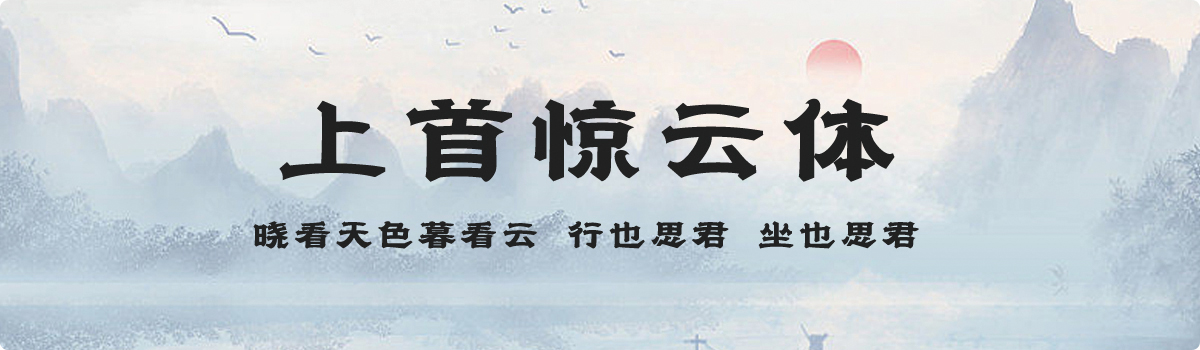
上首惊云体
上首惊云体,这款字体结构工整、笔画清晰,兼顾美观与易读性,适用于标题、正文、海报、包装、LOGO 等多种场景。字形优雅稳定,风格百搭耐看,适配日常排版与创意设计,让文字呈现更舒适、更具质感。上首惊云体一笔一画,皆是细节,以均衡的比例、流畅的线条打造舒适视觉体验,字形端正大气,风格简约现代。无论是商业设计、品牌宣传还是日常排版,都能轻松驾驭,让文字更有格调与力量。上首惊云体字体下载。